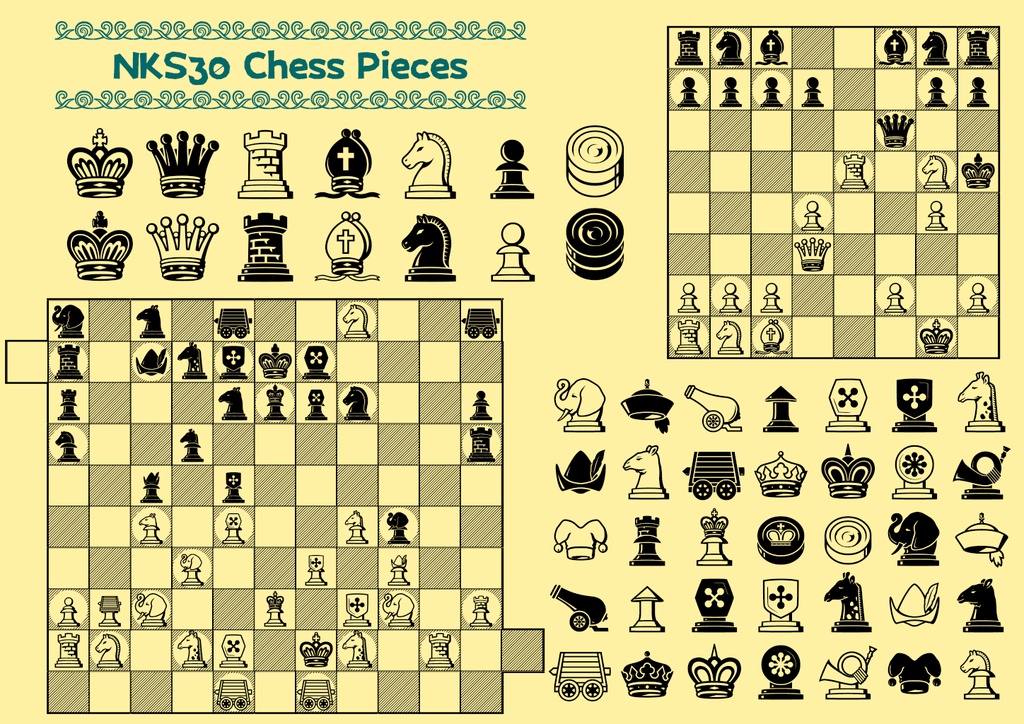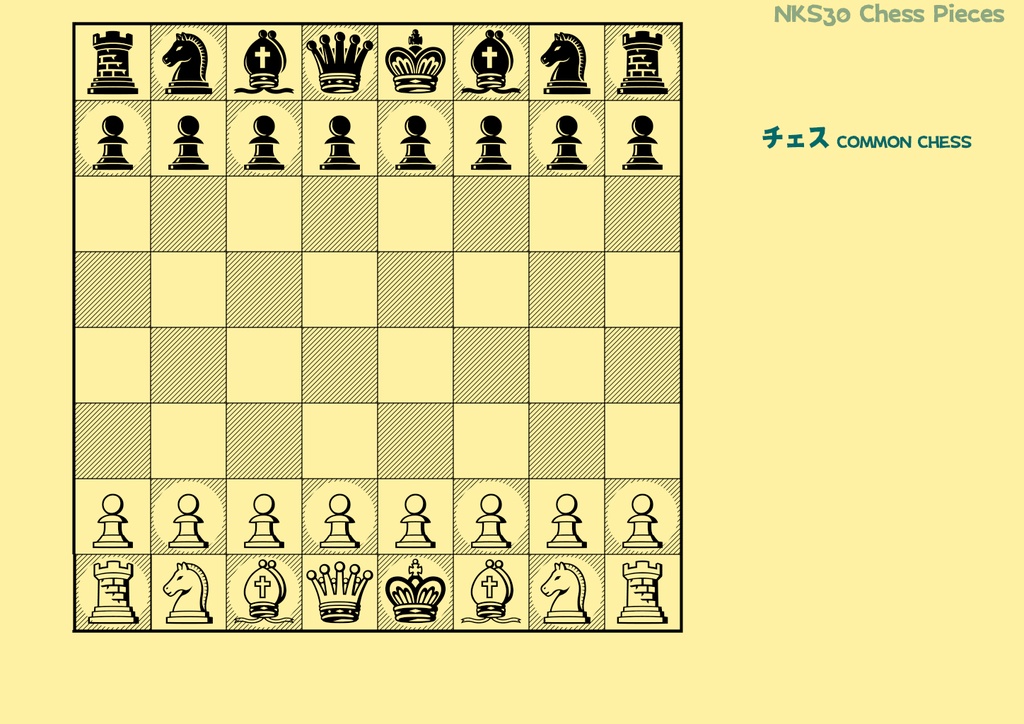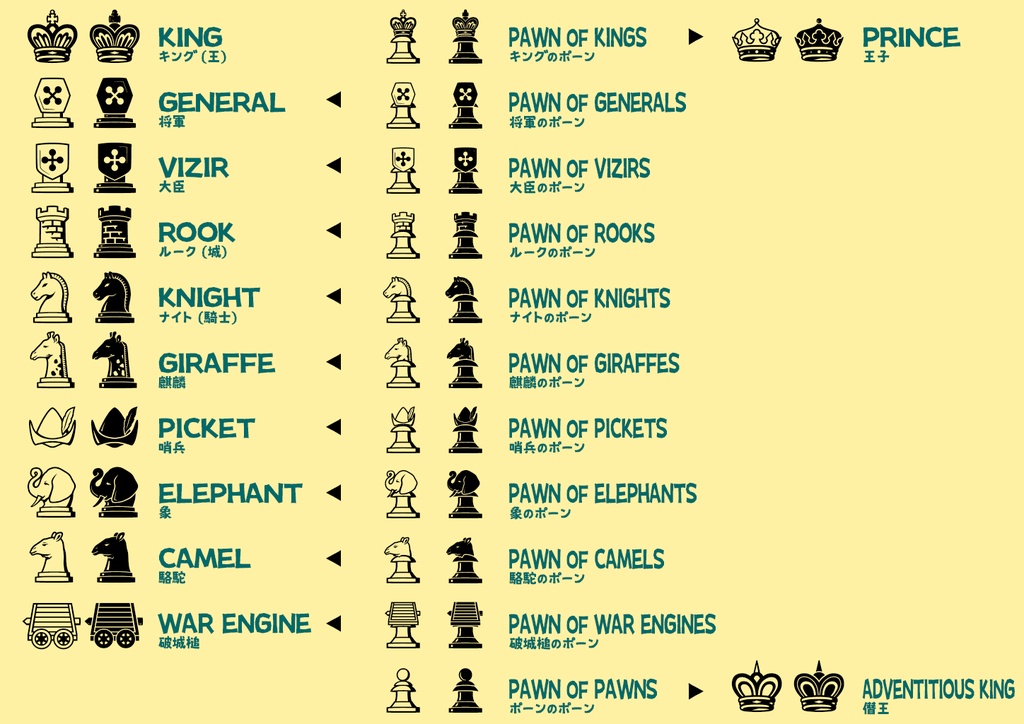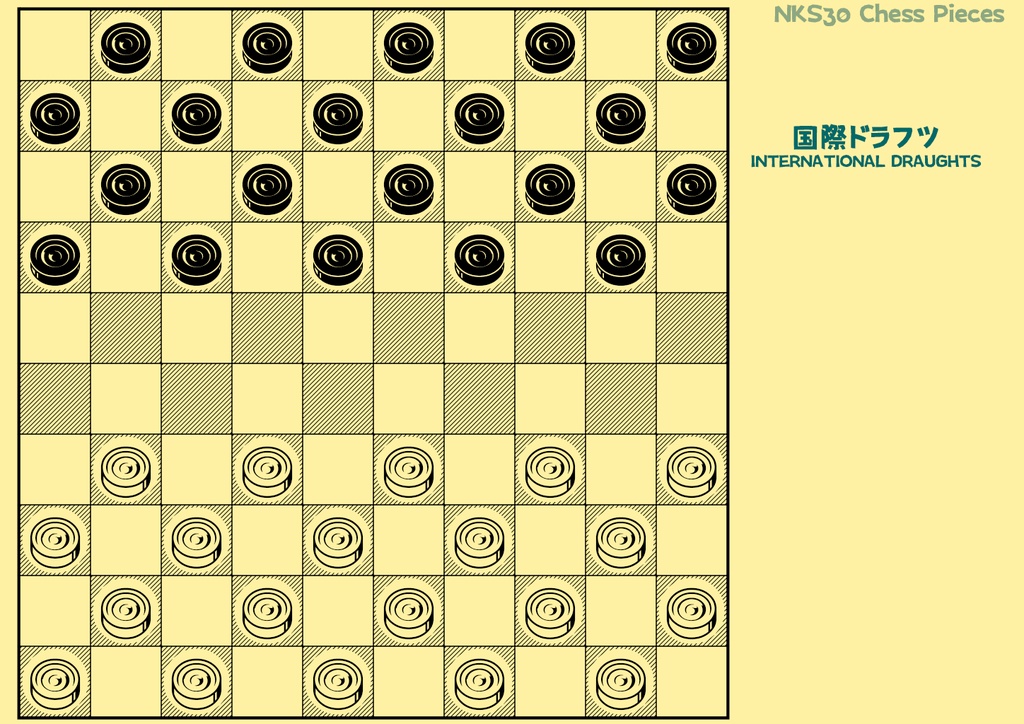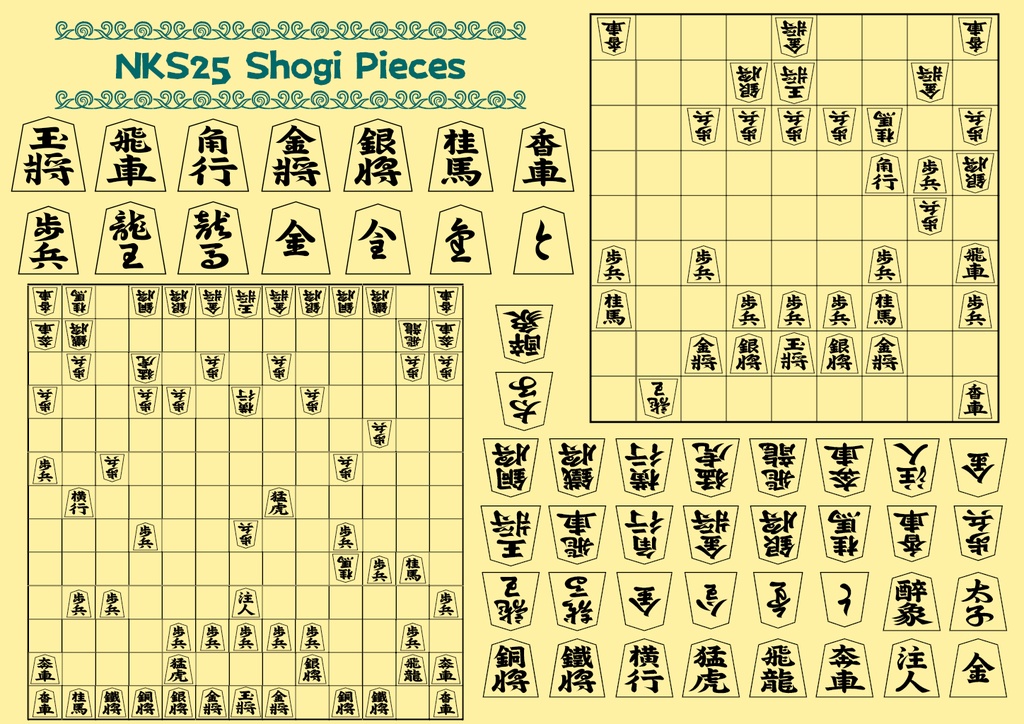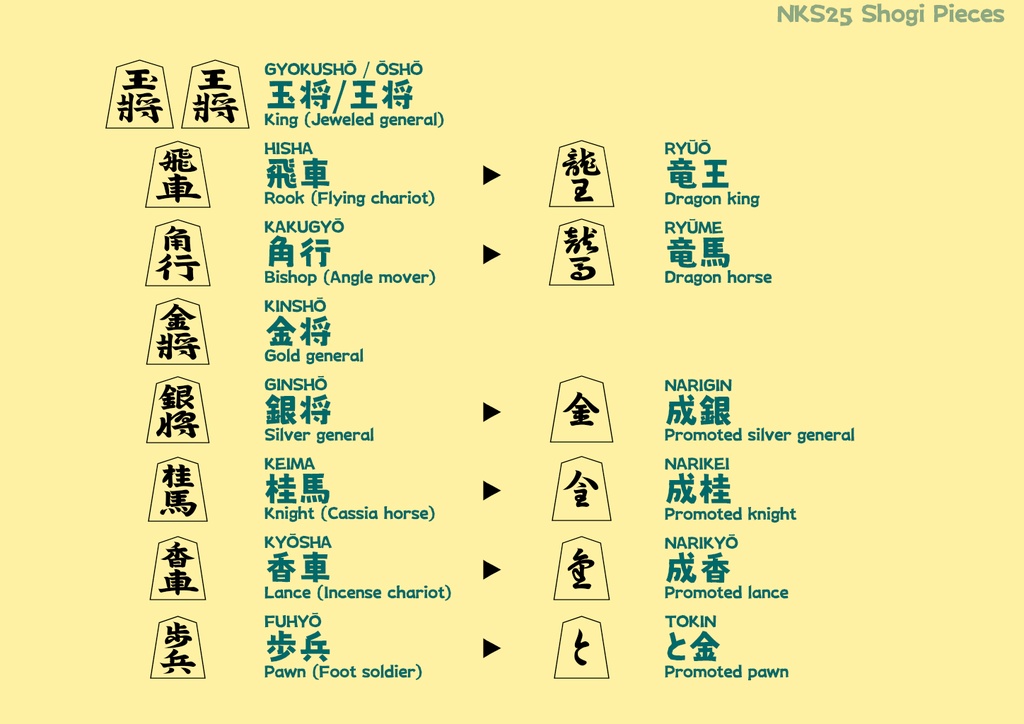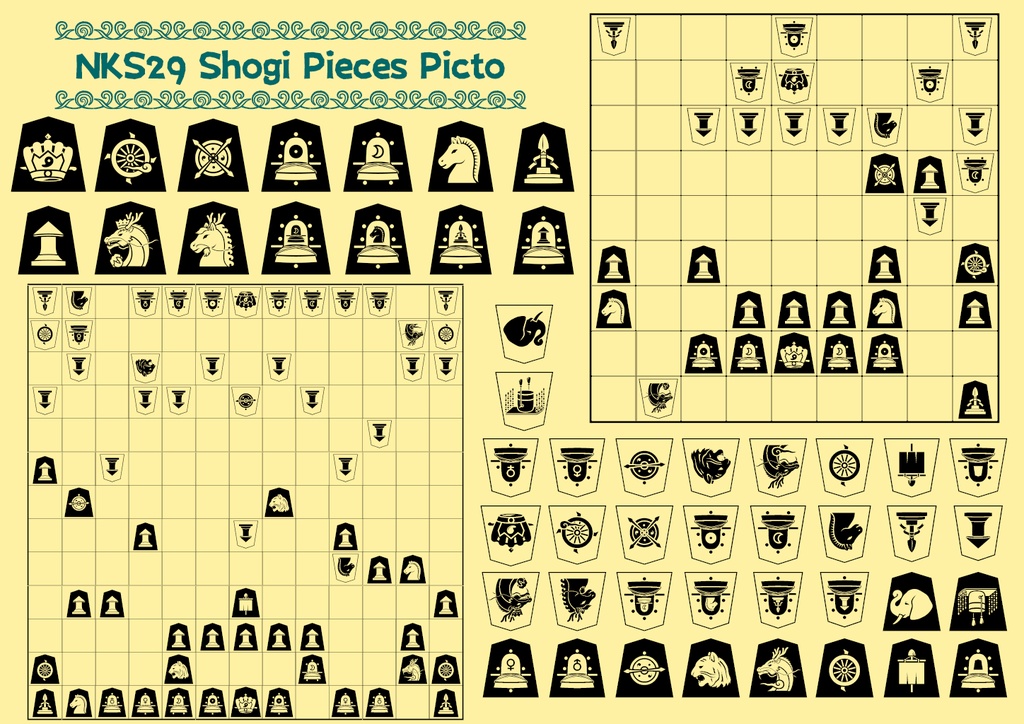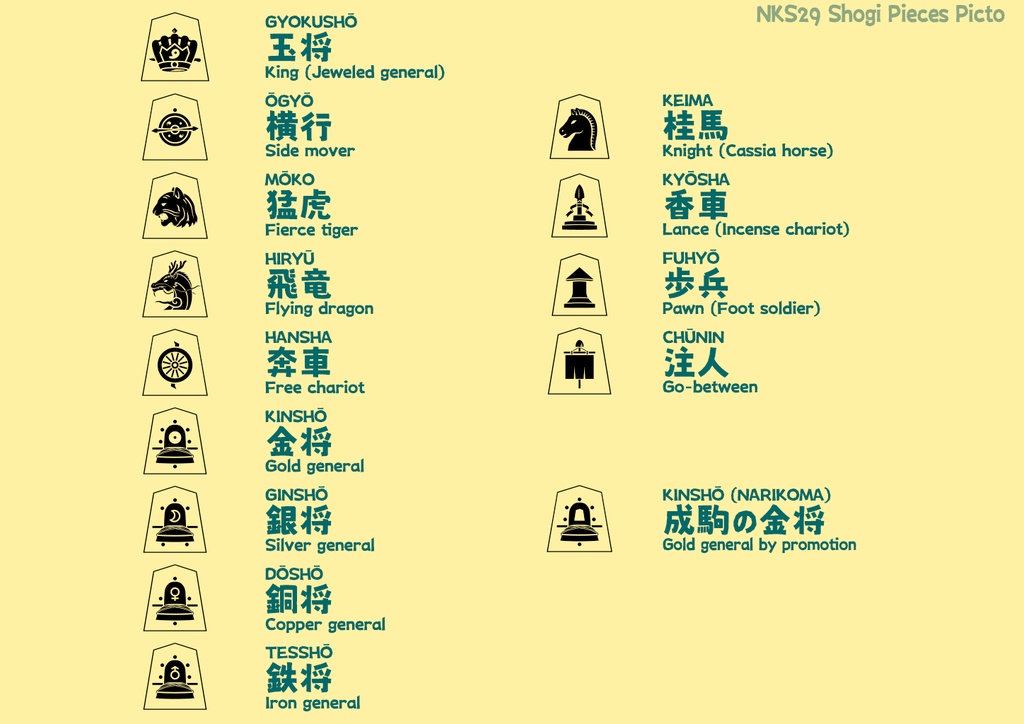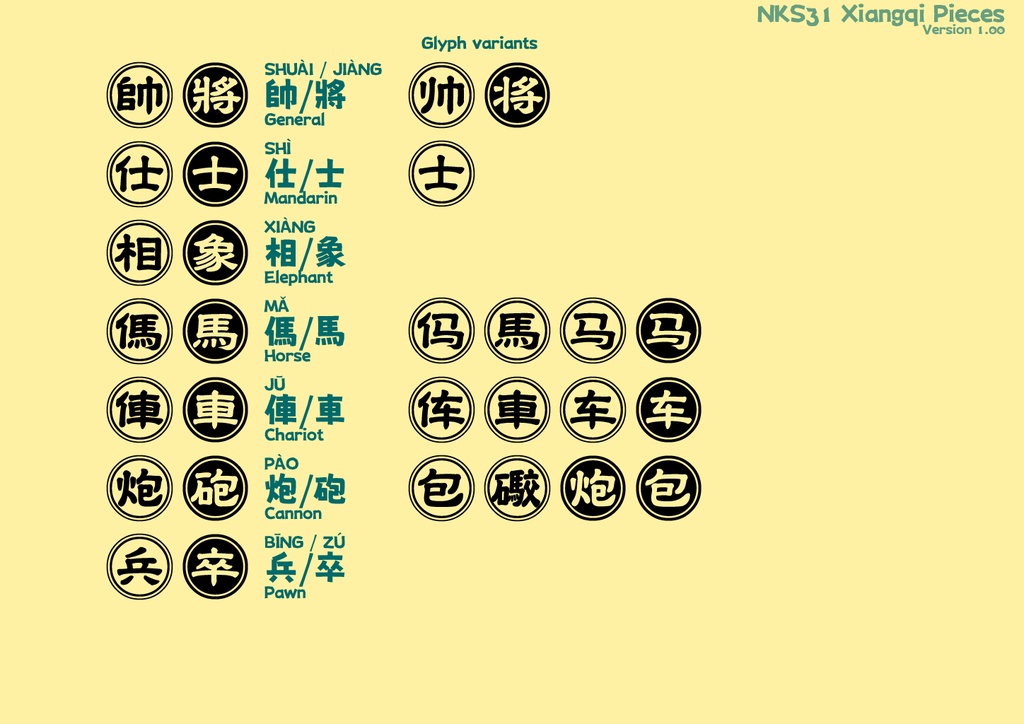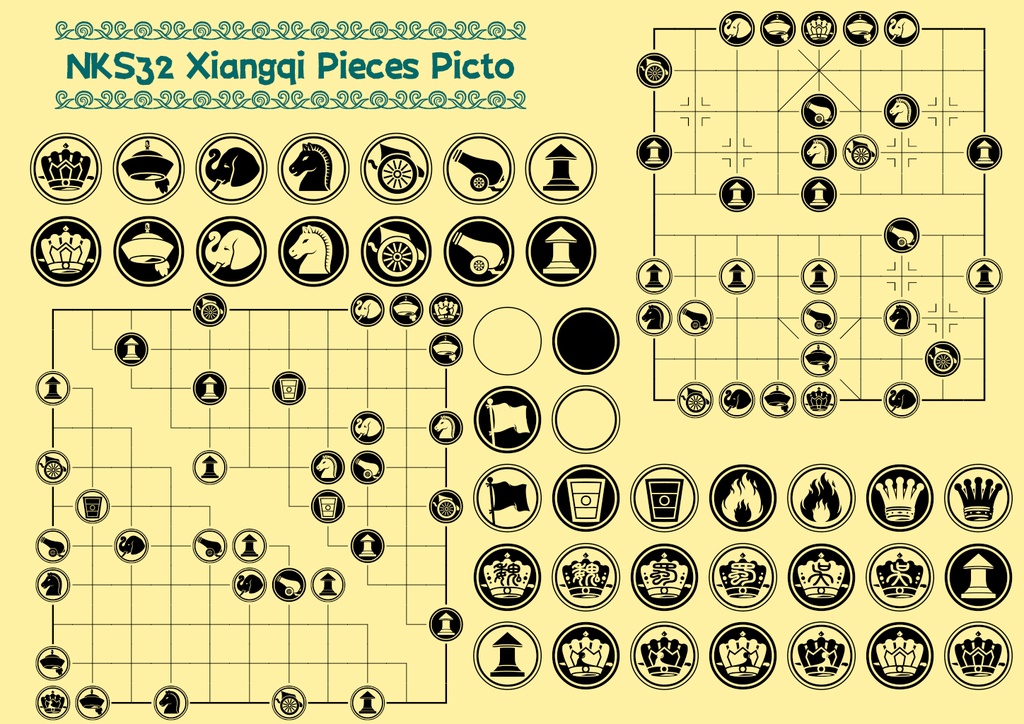
波間のかけひきフォント集・世界象戯伽藍 第一輯
NAMIMA NO KAKEHIKI FONT COLLECTION - THE TABERNACLE OF THE CHATURANGA LINEAGE: VOLUME I 🔤 独自にデザインした世界各地のチェス・将棋類の駒のフォント集です。 西洋チェス、ペルシアのチェス、ドラフツ、日本将棋、中国象棋、タイのマークルック、ならびにそれらの亜種などの駒を幅広く収録。グリフを並べることで盤面の描画もできます。 主にラテンアルファベットの領域や、私用領域(外字)のところにグリフを収めています。 ❖ 当フォント群の一般的な目的での使用 (文書や画像の作成、装飾としての利用など) は私用、同人、商用を問わずご自由にどうぞ。 ✽ 形式: フォントはTrueType、添付資料はPDF
収録フォント群
❖「チェスの駒」 NKS30 Chess Pieces Squared ❖「将棋の駒」 NKS25 Shogi Pieces Squared ❖「将棋の駒・象形」 NKS29 Shogi Pieces Picto Squared ❖「象棋(シャンチー)の駒」 NKS31 Xiangqi Pieces ❖「象棋(シャンチー)の駒・象形」 NKS32 Xiangqi Pieces Picto ❖「マークルックの駒」 NKS33 Makruk Pieces Squared